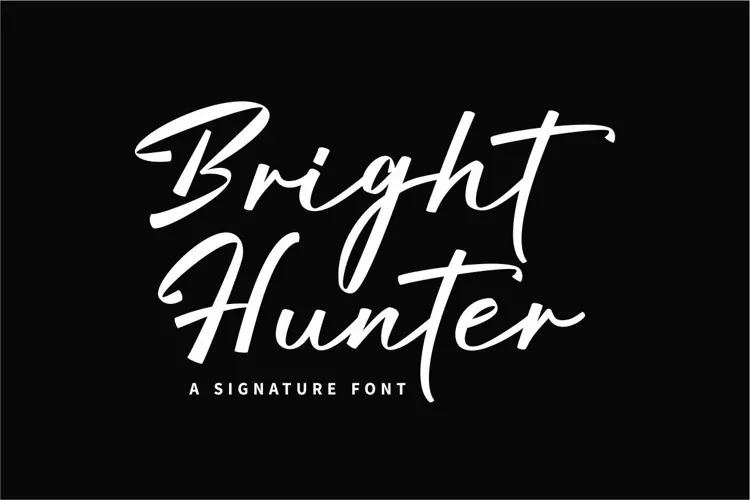
A fonte ‘Bright Hunter’ é uma escolha ideal para designers que procuram um charme natural e despojado para suas criações digitais. Desenhada pela GFR creative, esta fonte script oferece um toque de simplicidade e equilíbrio nos traços, característica única dos escritos manuscritos. Ideal tanto para textos mais formais quanto para estilos mais leves, ela proporciona uma aparição de texto relaxada que se adapta perfeitamente a vários tipos de projetos. Com seu design asymmetrical (desproporcional) e sua forma suave e elegante, ‘Bright Hunter’ torna-se não apenas um elemento versátil para criações digitais, mas também um complemento gráfico perfeito para qualquer trabalho que você estiver desenvolvendo. Este é o tipo de fonte com a qual você pode inovar, transformando seus projetos em algo único e cheio de personalidade.